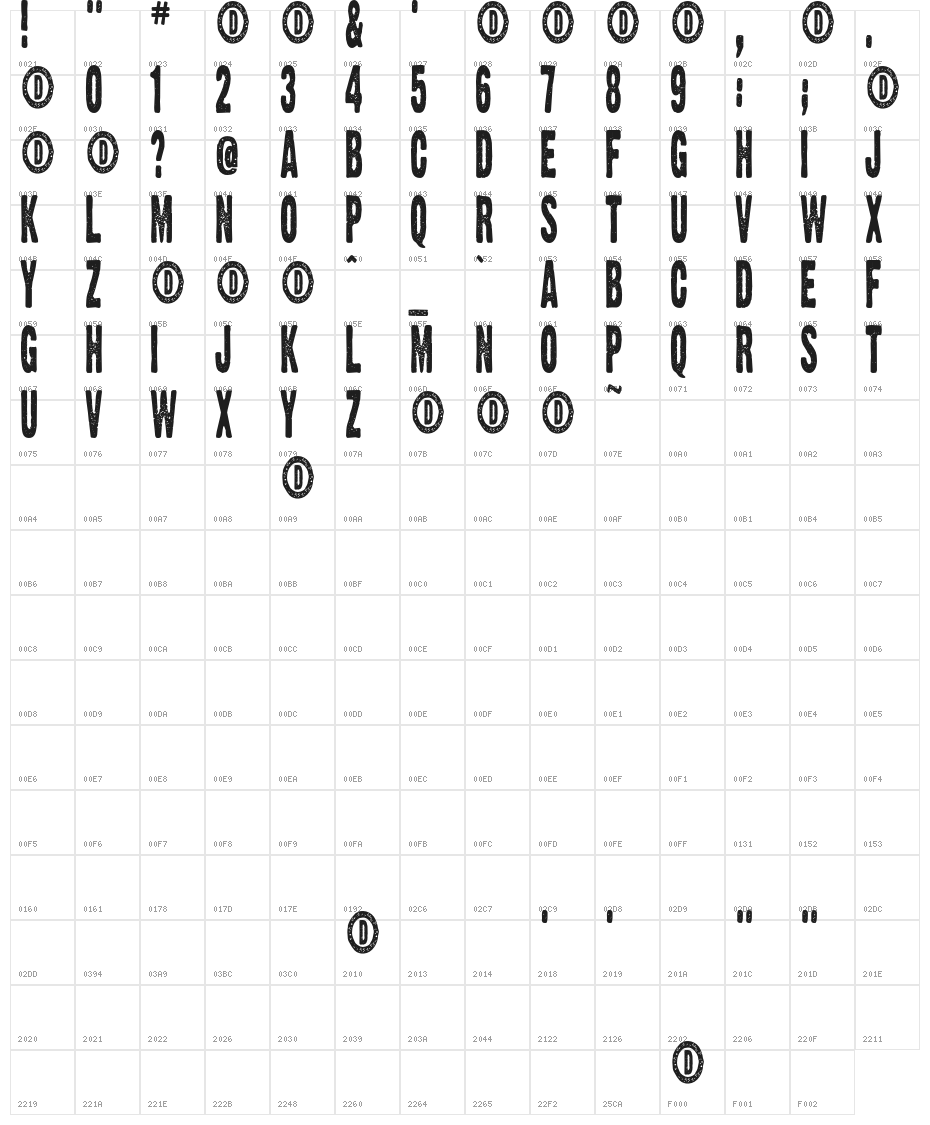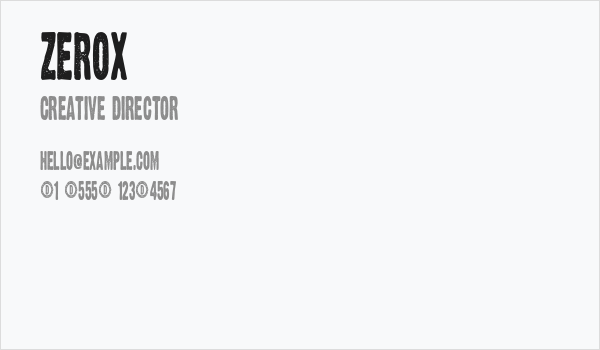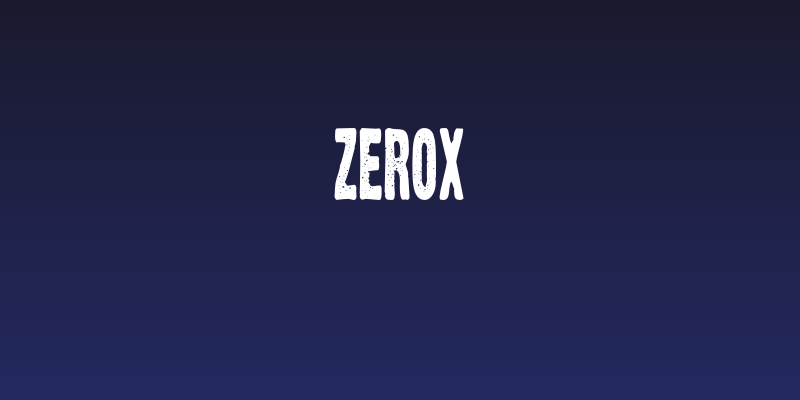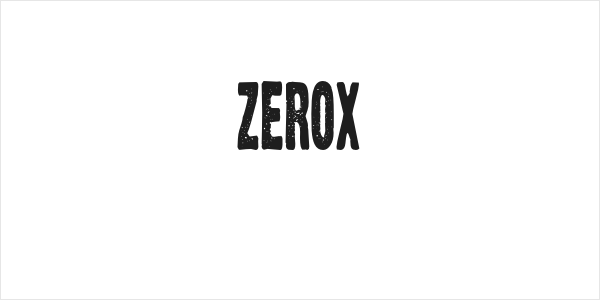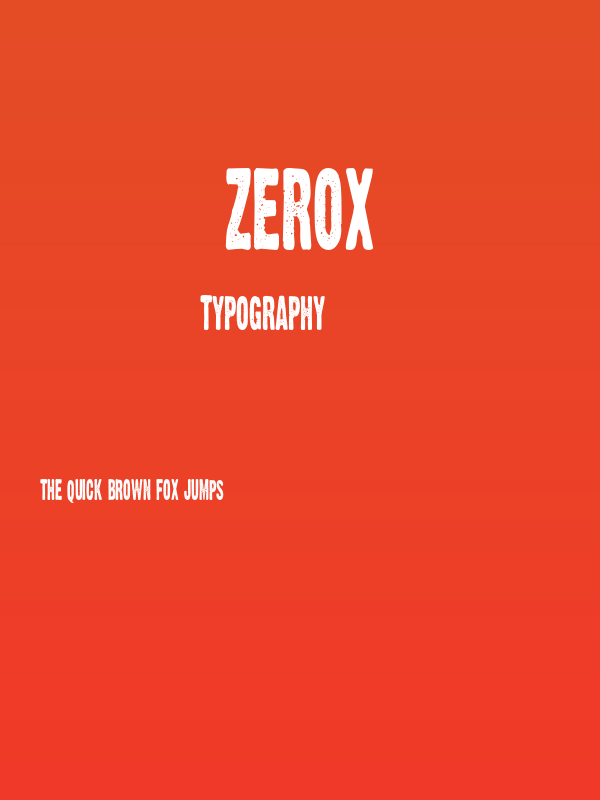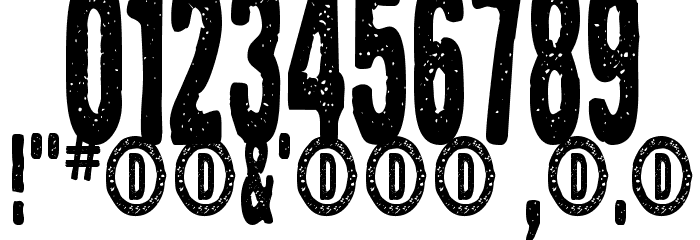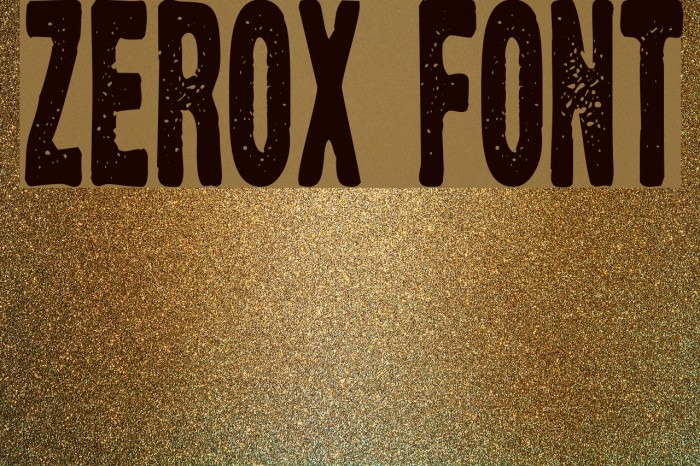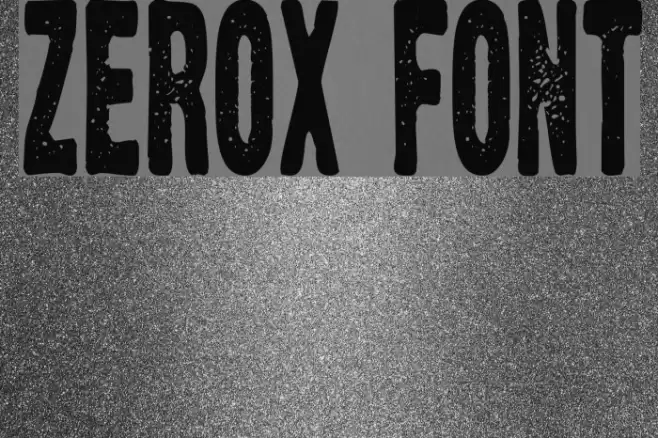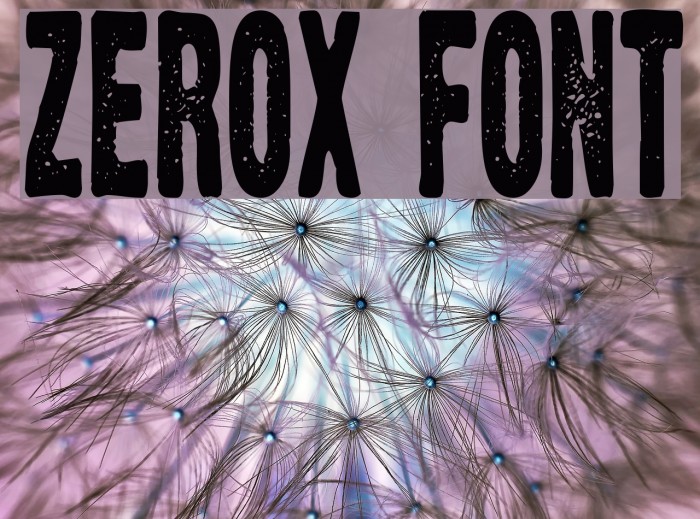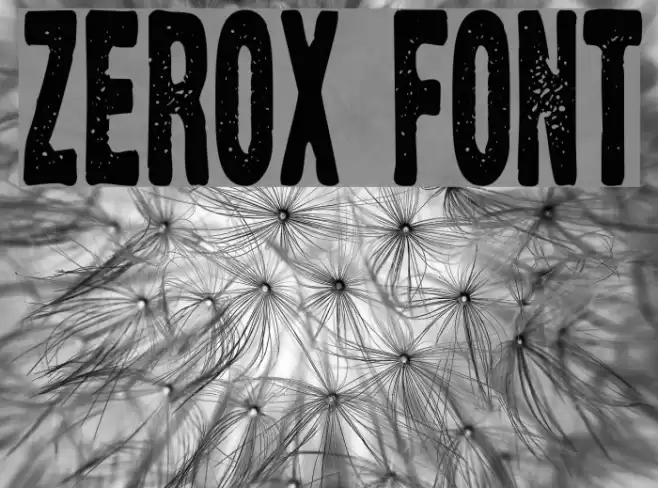
Zerox Font
✎ Messy
| Proiecte propuse | Ideal for posters, album covers, branding for vintage-themed products, and any design requiring a grunge or worn look. |